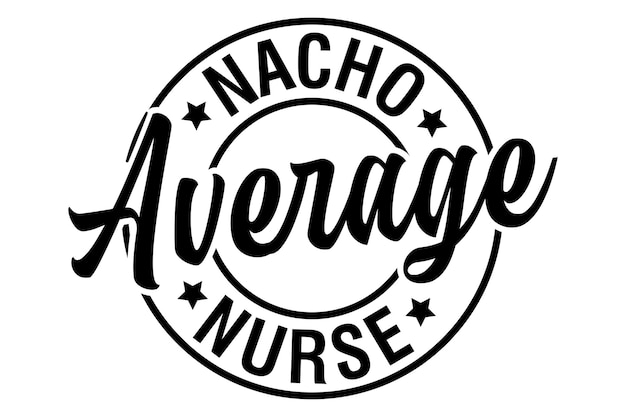
Logo de lettrage écrit à la main Nachos, étiquette, insigne, emblème, signe pour le menu du restaurant mexicain, insigne de café. Style rétro vintage. Calligraphie moderne, typographie. .